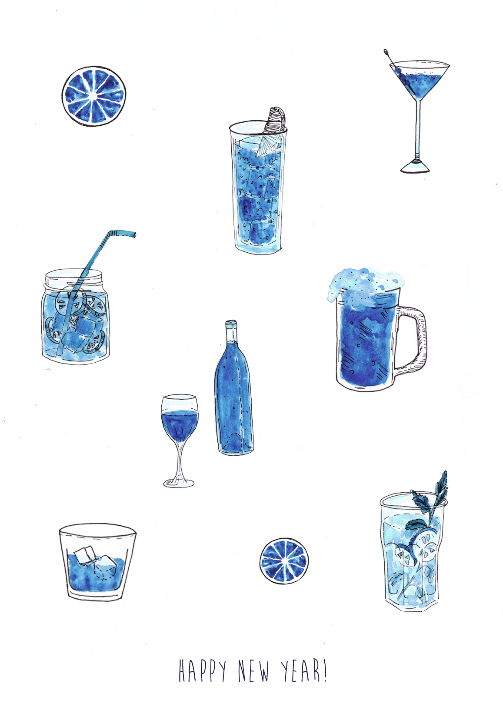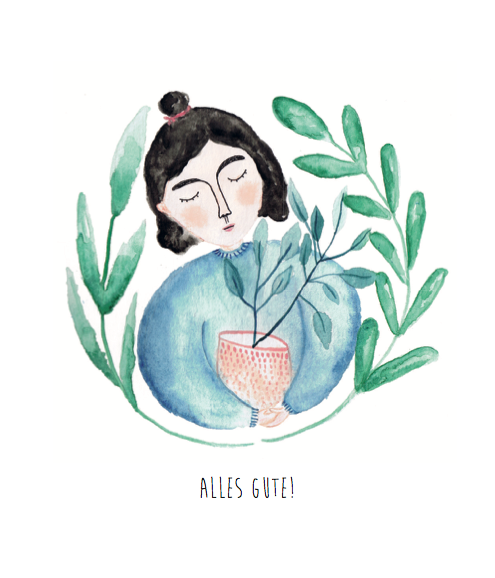
Welche Fließtextschrift zu Handdrawn Fonts wie Brain Flower oder Amatic
Ich bin Illustratorin und benutze gerne Handdrawn Fonts wie Brain Flower oder Amatic
Leider fällt es mir sehr schwer die passende Fließtextschrift zu finden.
Die Schrift soll zu meinen Illustrationen und zu den beiden Schriften passen. Sie soll
ästhetisch und klar sein und gut lesbar. Ich brauche sie für Informationen auf Stickern und
Flyern und am besten auch für meine Website.